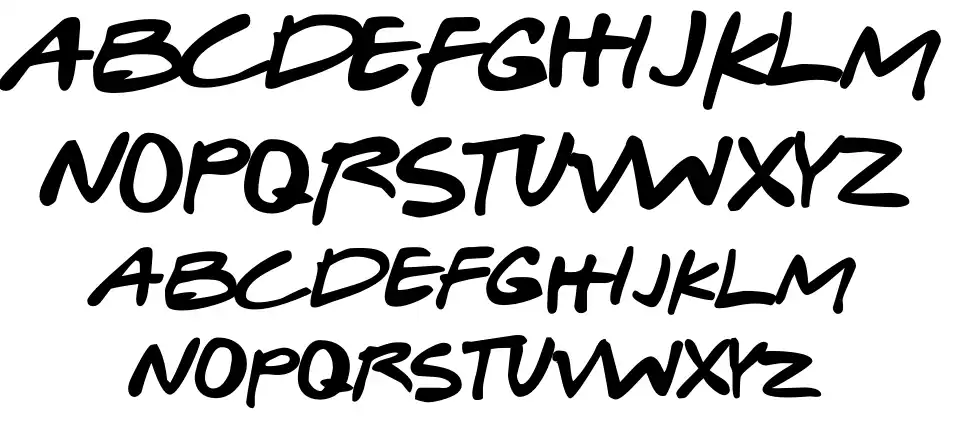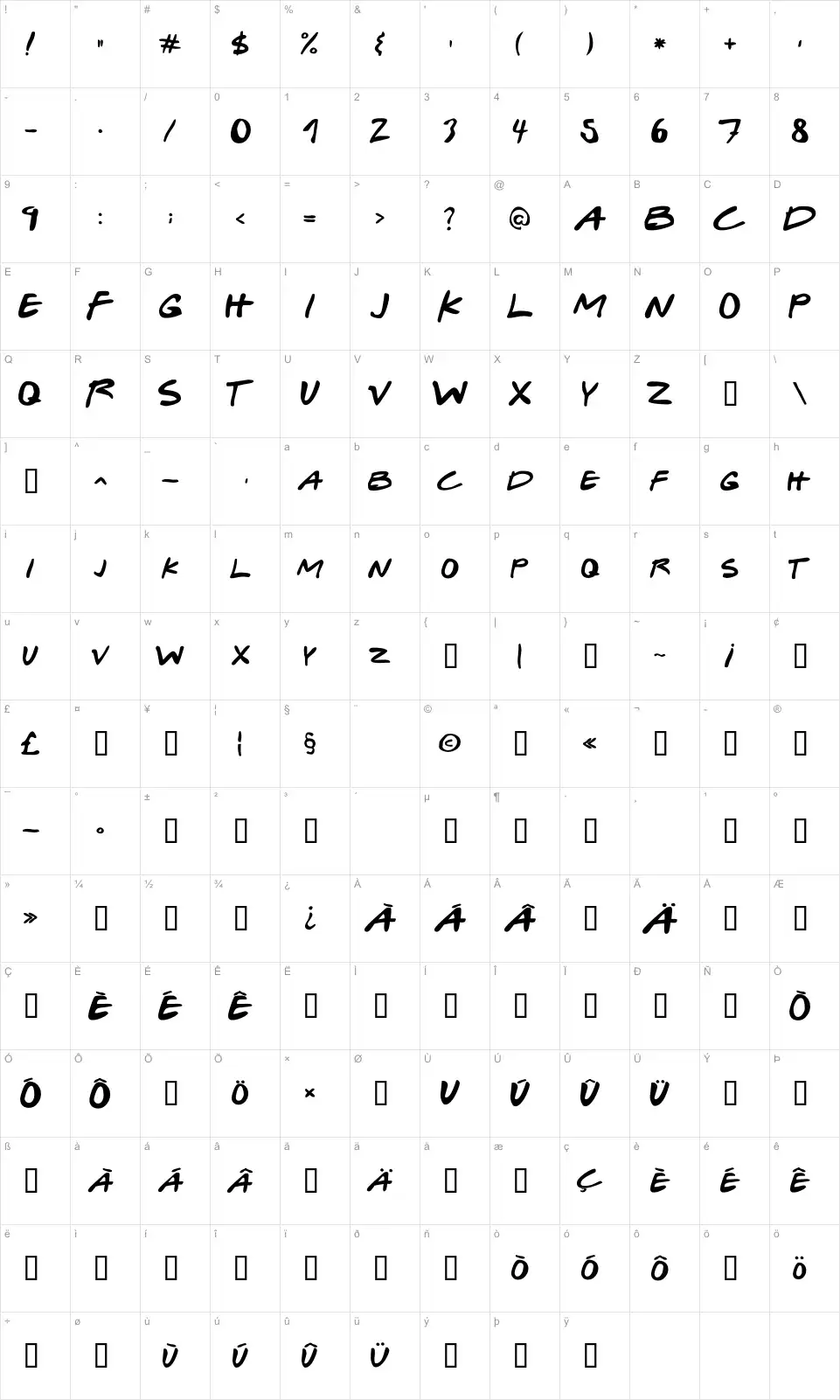
A fonte Gabriel Weiss’ Friends é um charmoso script handwritten que combina naturalidade e elegância. Desenvolvida pelo próprio Gabriel Weiss, esta fonte é perfeita para um estilo casual e descontraído, seja para um design de logotipo, arte digitais ou qualquer outra necessidade de texto. Se você está procurando uma fonte que seja ao mesmo tempo versátil e única, Gabriel Weiss’ Friends pode ser uma ótima escolha. Desfrute de sua versão gratuita e personalize o preview de texto online para ver como ela se assemelha à fonte original. Esta font foi adicionada em 12 de julho de 2022 e já foi baixada pelo menos 6165 vezes, mostrando seu valor e popularidade. Com seu tamanho compacto de 15 KB, Gabriel Weiss’ Friends é um download rápido e de alta qualidade que você não pode deixar de experimentar.
Categoria: Script › Handwritten
Designer: Gabriel Weiss